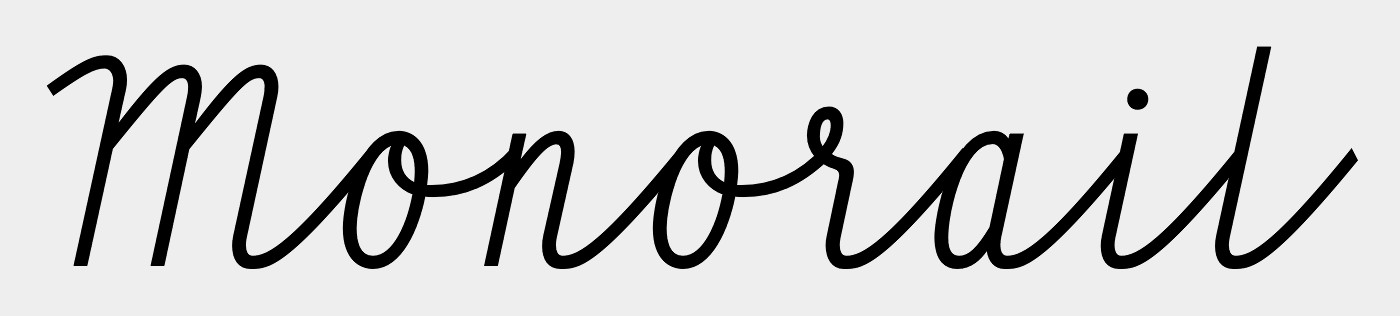
ich suche typen, die ich als »konstruierte« scriptschriften deklarieren würde. mich würde interessieren welche beispiele dazu auftauchen könnten, da mir selber leider keine konkreten dazu einfallen. als sozusagen »vorlagen« dient mir wiedermal lediglich ein schnipsel einer art handgezeichneten logotype:
schriften die ich suche würden in diese richtung tendieren, also nicht unmittelbar eine pinselduktus aufweisen, sondern von der formensprache linearer, vielleicht geometrischer und weniger manieriert sein.
ah genau, easyscript von lineto geht in die richtung was ich suche!
gibt es noch mehr derartige monolineare scriptschriften die sich eher dem geometrischen annähern?
die FIG script ist fein.
von jonathan b. sagt mir nur die sarcastic zu.
soda script leider auch zu weit weg.
die HT profumeria is zu glatt und fedrig. die type die ich suche sollte bewusst diesen geometrisch konstruierten charakter aufweisen.
bisherige favoriten: easyscript, FIG und sarcastic — für weitere empfehlungen bin ich sehr dankbar.